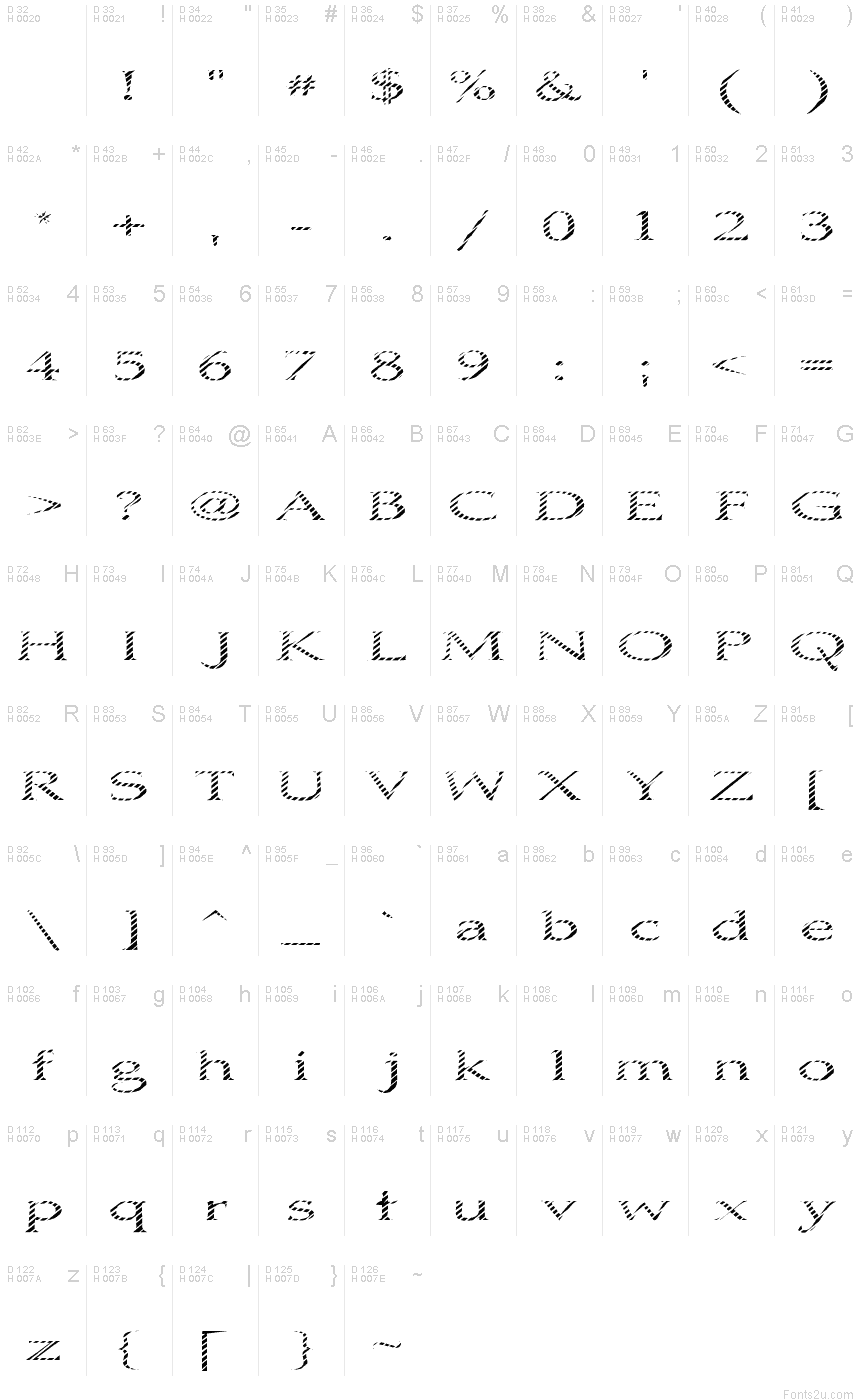
Boldly Go od GemFonts98 to darmowy, dekoracyjny krój szeryfowy o kinetycznej, prążkowanej teksturze, która sprawia wrażenie, jakby litery wibrowały na stronie. Każda litera jest wycięta w ukośne pasy, co tworzy wrażenie ruchu i energii, zachowując przy tym wyraźną i czytelną sylwetkę. W efekcie uzyskujemy odważny, nieco futurystyczny wygląd, który jest jednocześnie zabawny i techniczny – niczym szyldy z retro-futurystycznego wesołego miasteczka.
Używając Boldly Go, dodasz wyrazistości plakatom, okładkom książek lub komiksów, miniaturom na YouTube, ulotkom wydarzeń, brandingowi projektów technologicznych lub gier oraz przyciągającym wzrok nagłówkom. Ten darmowy font najlepiej sprawdza się w większych rozmiarach, gdzie jego detale mogą w pełni wybrzmieć; w tekście głównym zestaw go z prostym, dyskretnym krojem bezszeryfowym, aby skupić uwagę na tych żywych, wzorzystych literach.